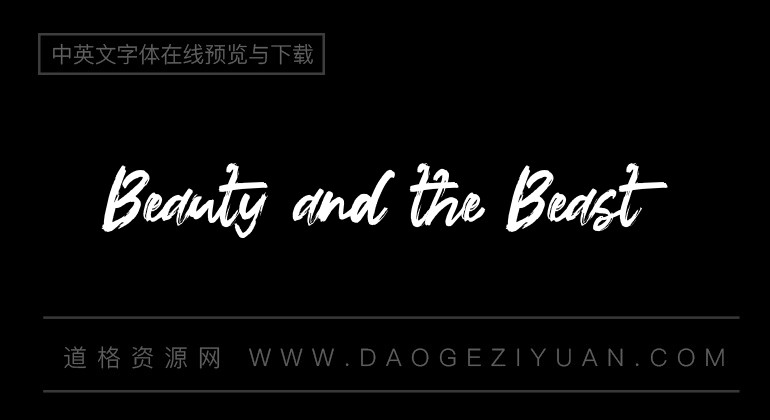
Beauty and the Beast
Beauty and the Beast 是一款英文字体,由著名的英国设计师 Ian Barnard 创作。它的特点是结合了新旧字体的元素,融合了经典的传统字体与现代的设计元素,具有浓厚的古典气息,充满着浪漫和浪漫主义的风格。它可以用于创作浪漫的文字,也可以用于创作经典的海报、插图、书籍封面等。
Beauty and the Beast是一款非常不错的手写艺术字体,具有很好的视觉感,适合于文化类的宣传设计、商业类品牌的广告和产品包装设计以及个性化文字排版等较多场景。